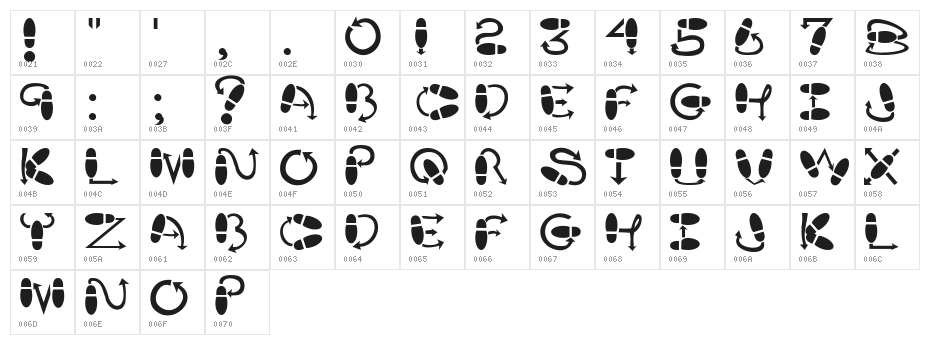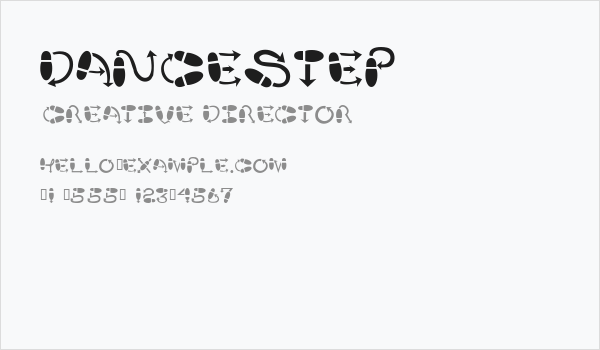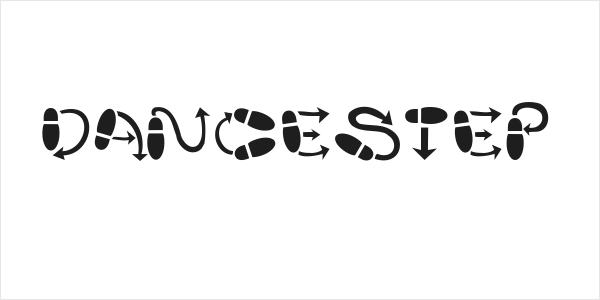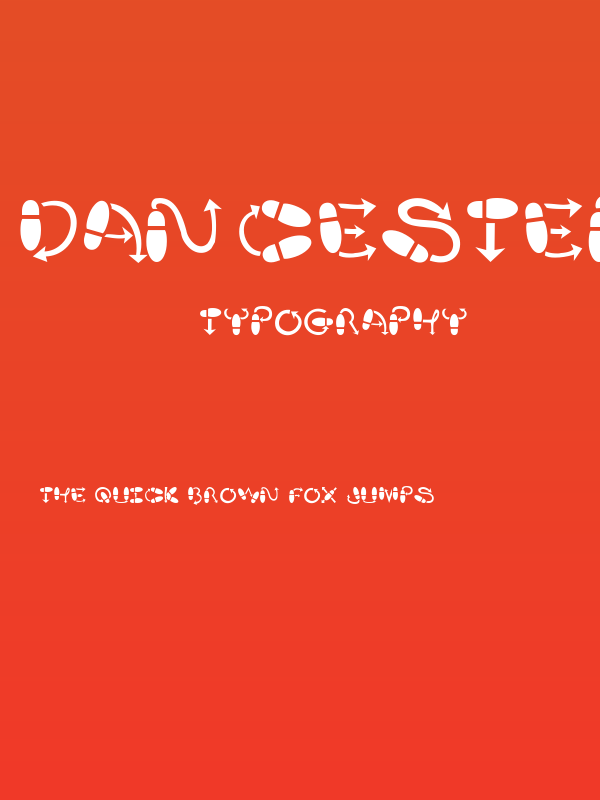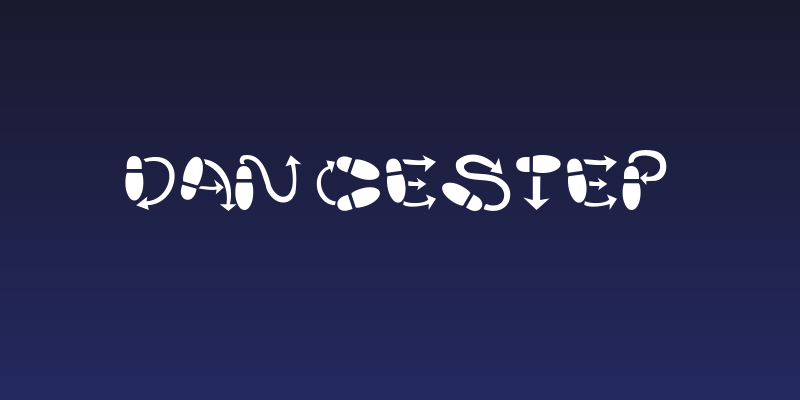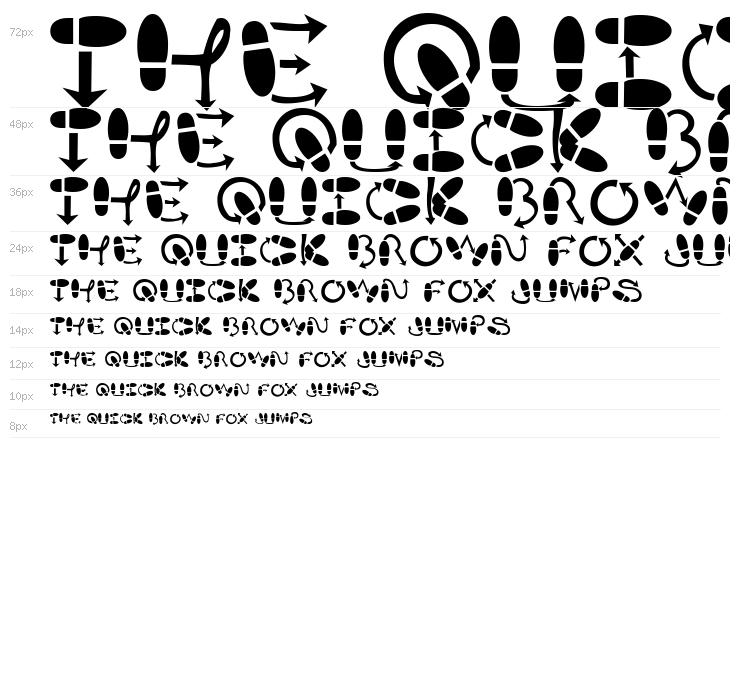
DanceStep Font
| Progetti proposti | Ideal for dance studio branding, event posters, children's party invitations, and any project needing a lively and energetic typeface. |